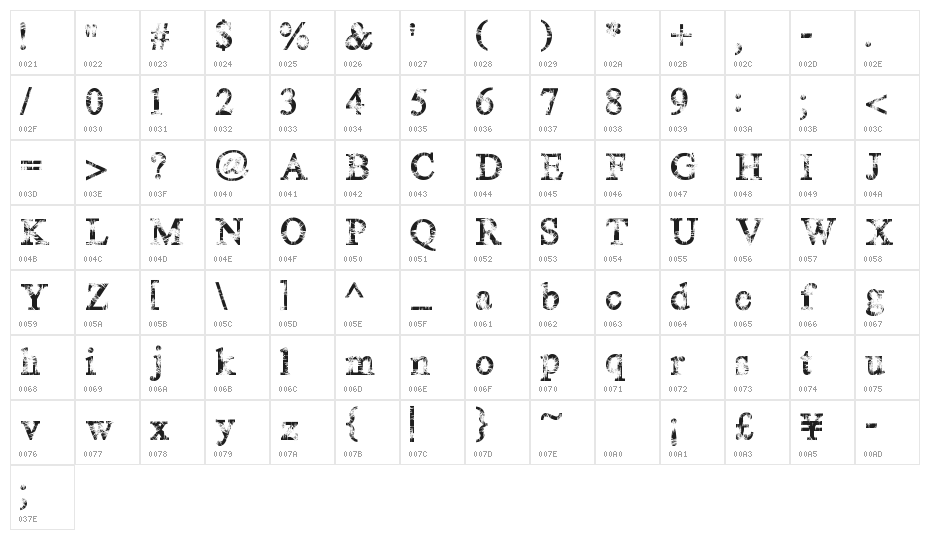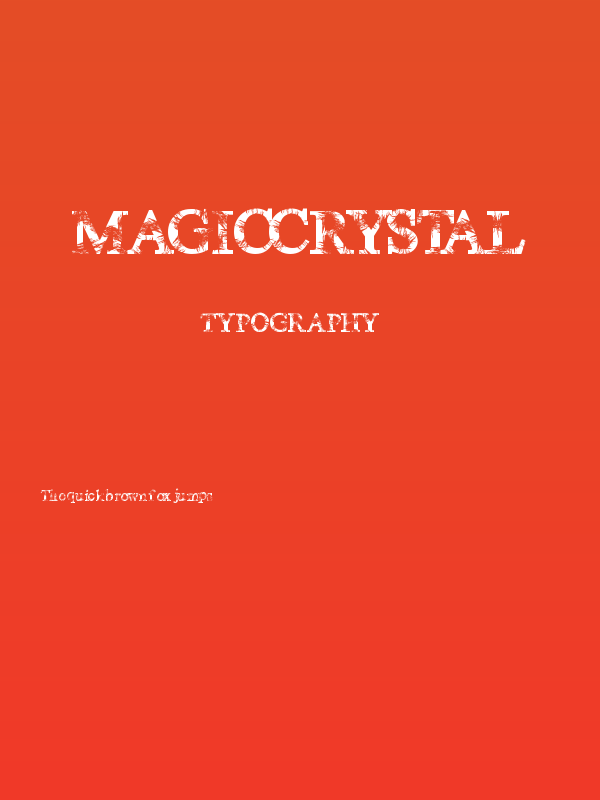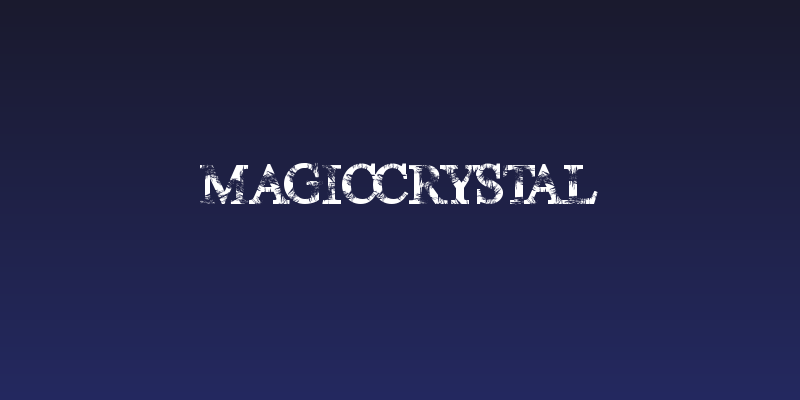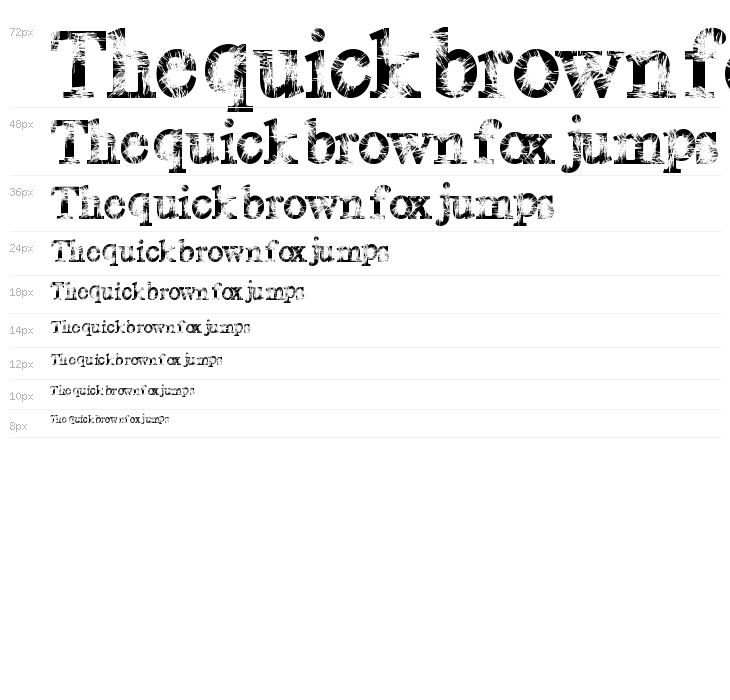
MagicCrystal Font
✎ Distorted Eroded
| Vorgeschlagene Projekte | Ideal for album covers, posters, branding materials, and any project needing a bold, artistic touch. |